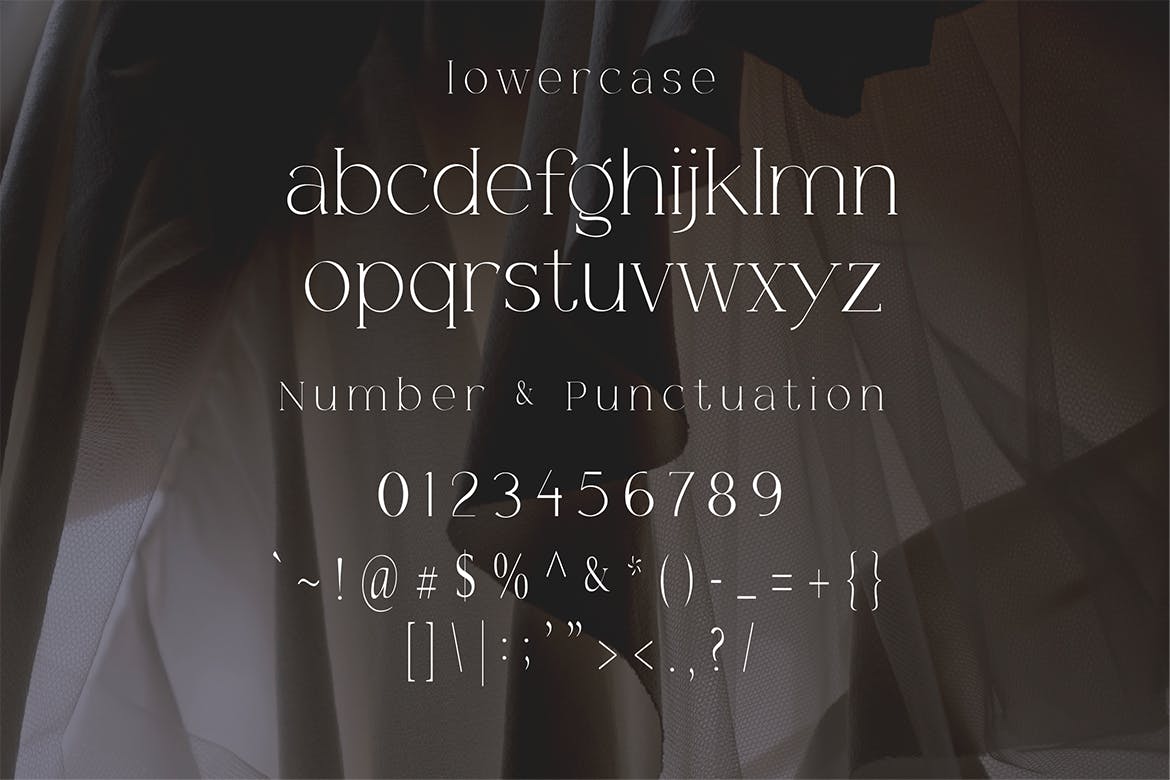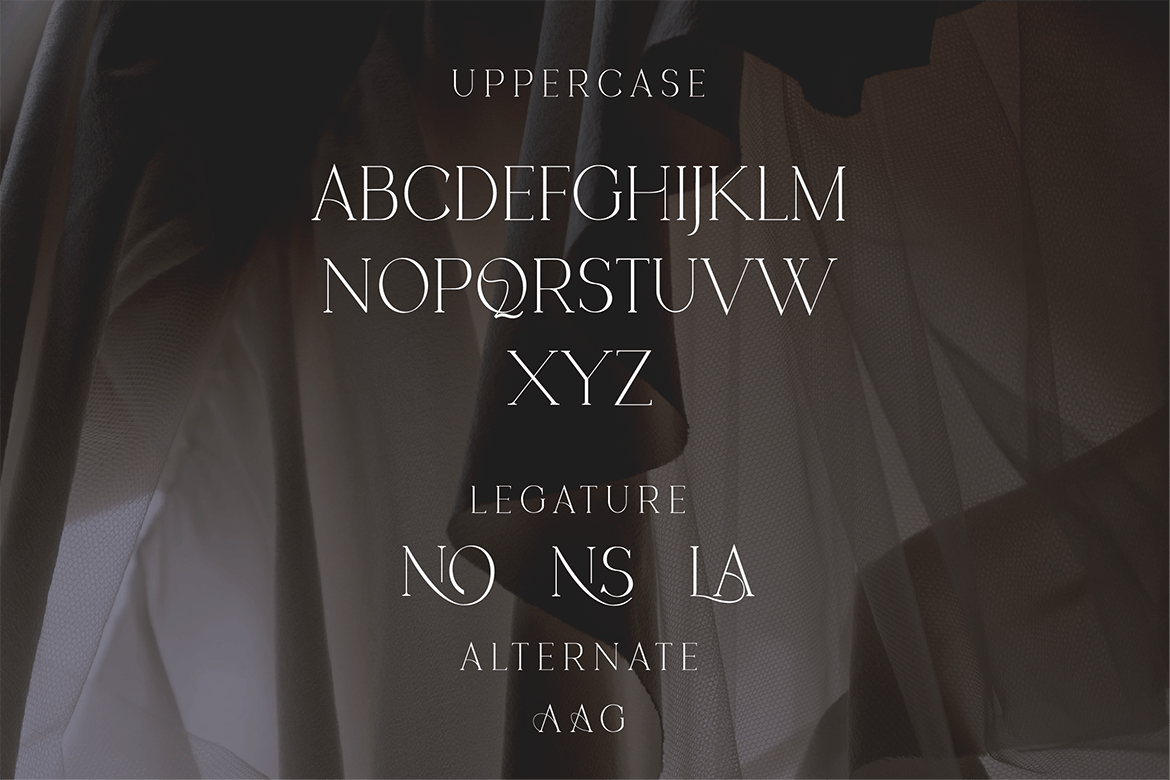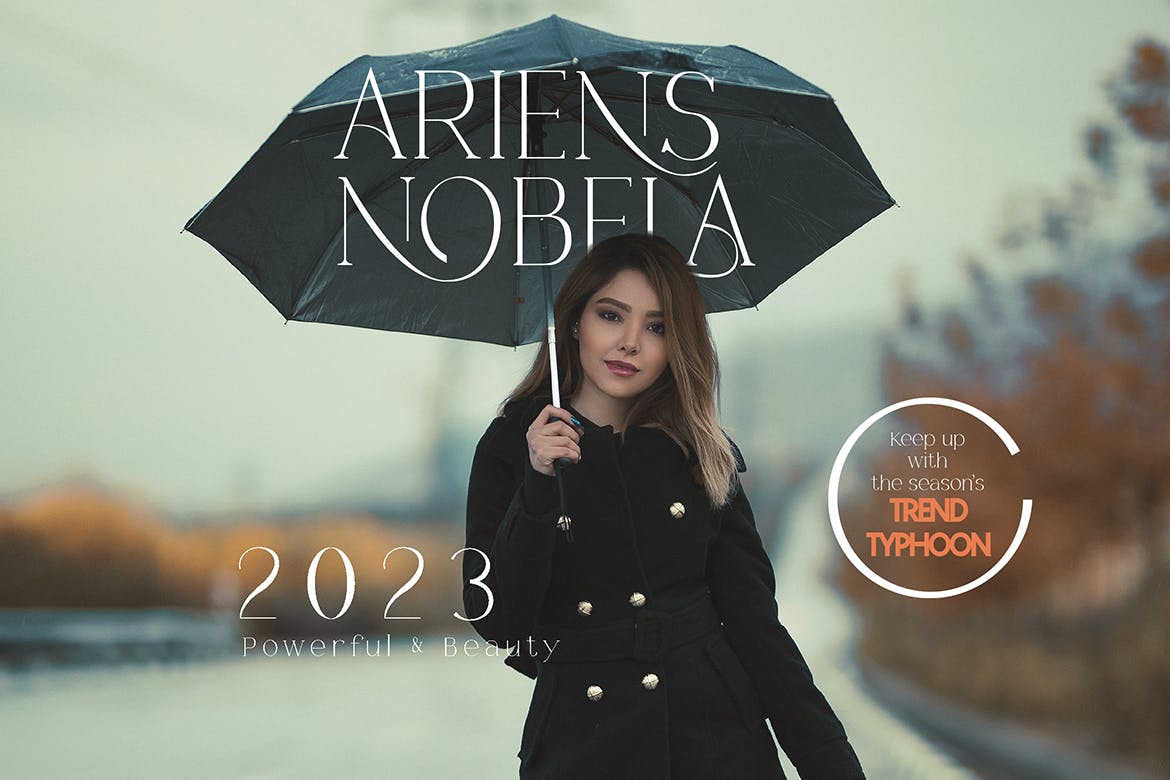
Ariens Nobela Luxury Font
فونت Ariens Nobela با طراحی زیبا و لوکس، انتخابی عالی برای پروژه‌های شماست.
معرفی Ariens Nobela، یک فونت سریف زیبا و لوکس که احساس منحصر به فرد و دلنشینی دارد. این فونت برای طراحی لوگو، مجله، رسانه‌های اجتماعی، بروشور و بسیاری پروژه‌های دیگر بسیار مناسب است.
• حروف بزرگ
• حروف کوچک
• اعداد
• نقطه‌گذاری
• لیگاتور زیبای NO، NS، LA
• نسخه‌های جایگزین برای A و G